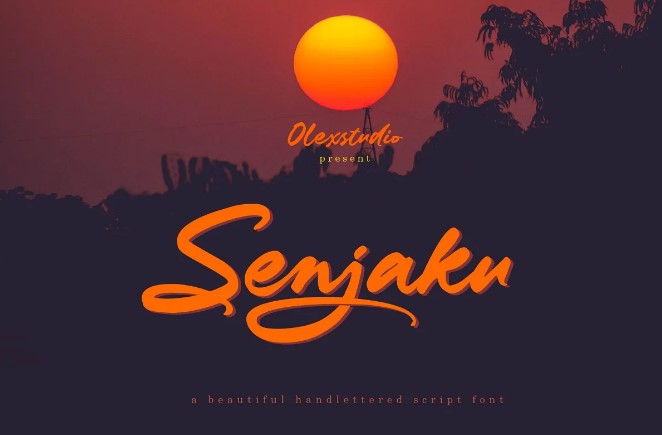
Creativemarket Senjaku - Handlettered Font
[Creativemarket] Senjaku Font
Senjaku - Handlettered Font будет великолепно смотреться на всех ваших дизайнах, приглашениях, дизайне плакатов, дизайне книг, брендинговых материалах, логотипах, футболках и всем дизайнерском оформлении проекта.